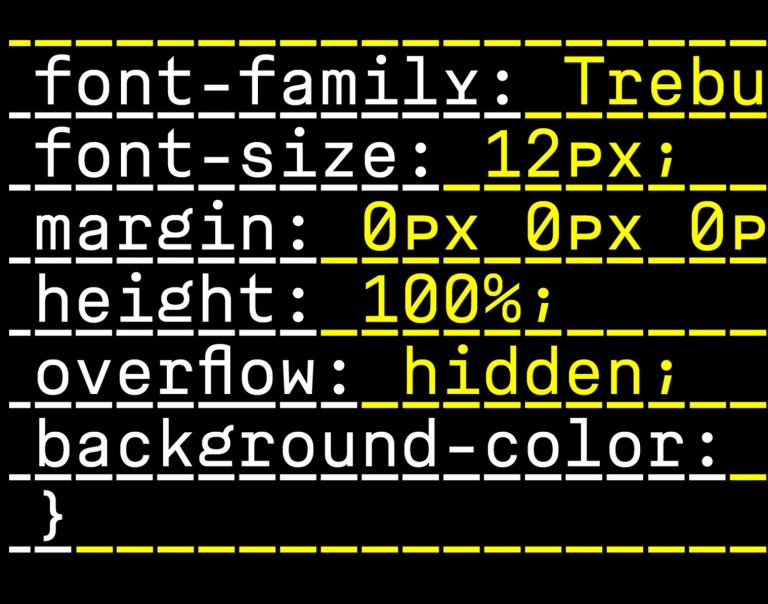
Tipografías monoespaciadas: la irresistible belleza del orden
ASM, diseñada por Íñigo Jerez.
Durante mucho tiempo han sido las letras más serias del mundo tipográfico, pero poco a poco, la percepción que tenemos de ellas ha ido cambiando y parece que ahora se han soltado definitivamente la melena. Pero empecemos por el principio.
Soy monoespaciada y también me divierto.
Ya lo dice su propio nombre: las tipografías monoespaciadas son aquellas cuyos caracteres ocupan siempre el mismo espacio, en contraposición a las tipografías de anchura variable o proporcional, donde los caracteres poseen tamaños diferentes entre sí. Las monoespaciadas encuentran su antecedente en las máquinas de escribir, en las que con cada impresión de letra tecleada el carro avanzaba siempre la misma distancia.
Son las tipografías usadas desde siempre por los programadores debido a que proporcionan gran legibilidad en un entorno donde una nítida identificación de los caracteres es de vital importancia. Por otro lado, en el plano meramente estético, se ha recurrido a ellas para dotar de cierto aire retro a según qué diseños, por ejemplo, rememorar el ambiente de la escritura a máquina de un original de guión de cine clásico.
Ser y no ser mono
Operator, diseñada por Hoefler & co.
Quizá, desde el punto de vista exclusivamente del diseño gráfico, su, digamos, rigidez, ha sido un escollo, aunque, por otro lado, siempre he pensado que aplicadas con gracia y en el lugar idóneo se convierten en una opción irresistible. Y no soy la única que lo piensa. En los últimos tiempos, tanto su diseño como su uso estético están cambiando, o, mejor dicho, están evolucionando y, por lo tanto, ensanchándose considerablemente sus posibilidades y prestaciones. Un muy buen ejemplo de ello viene de la mano de la fundición tipográfica norteamericana Hoefler & Co., que nos sorprendió a principios de este año 2016 con Operator, una tipografía con todo el espíritu de las monoespaciadas, pero sin las limitaciones mecánicas de éstas, es decir, eliminando el ancho fijo y permitiendo que los caracteres adopten sus proporciones naturales. Operator está compuesta por una completa familia opentype de nueve pesos con sus respectivas y sorprendentes cursivas.
Operator es toda una pirueta tipográfica: una monoespaciada que no es una monoespaciada.
Y para completar, aún más si cabe, la jugada, Hoefler & Co. no se han detenido ahí y han puesto la guinda al proyecto aunando las necesidades tanto de diseñadores como de programadores con la Operator Mono, una refinada destilación de las monoespaciadas puras que resulta perfectamente idónea para programar con estilazo o para diseñar matemáticamente.
De la misma manera que las fundiciones están ampliando el abanico de posibilidades de las monoespaciadas manipulando su ADN, los diseñadores están ampliando su utilización en campos donde era poco frecuente encontrarlas, dando lugar a diseños audaces y frescos.
Mi fijación con las monoespaciadas viene ya de lejos, pero se hizo más fuerte gracias al diseño de packaging de la línea de productos Body Luxuries de la marca Suavinex, realizados por el Estudio Mllongo. Me sedujo de ellos la utilización de una monoespaciada junto con una tipo de serifa en mayúsculas en los envases destinados a una línea de cosméticos para bebés y mamás, combinación nada habitual en este tipo de productos.
Línea de packaging Body Luxuries de Suavinex diseñada por Estudio Mllongo.
Packaging Body Luxuries de Suavinex diseñada por Estudio Mllongo.
El resultado, un diseño audaz y memorable, que marca la diferencia con otros productos de su segmento y que, por lo tanto, resulta muy original, pero sin perder, en mi opinión, ni un ápice de dulzura. A partir de ese momento, mi ojo de diseñadora tipópata, ya no podía ver nada más que monoespaciadas por todas partes.
Monoespaciadas everywhere.
Inconsolata, Courier, Apercu Mono, Letter Gothic, Andale Mono, Pica 10 Pitch, Greta Mono, Asm, GT Pressura mono, Pitch… Éstas son algunas de mis preferidas a la hora de combinarlas con otros estilos. Todas ellas me parecen muy versátiles, muy todoterreno. Bien usadas, funcionan realmente bien tanto en diseño web como en diseño de marcas, en diseño editorial y, como hemos visto, pueden quedar estupendamente en packaging. Vamos a verlo por partes.
Personalidad mono
A pesar de lo inquebrantable en su espaciado, la estética de una monoespaciada, esa supuesta rigidez que decía un poco más arriba, puede ser una gran ventaja y resultar absolutamente comunicativa, llegando a expresar de manera precisa y clara lo que la marca necesita para diferenciarse.
Aire web
Que la legibilidad de las fuentes monoespaciadas resulta vital en programación ya lo sabíamos, pero servidora desconocía la importancia de las ligaduras para mostrar caracteres más «entendibles» para los desarrolladores de código. Gracias a que mi trabajo como diseñadora me ha dado la oportunidad de colaborar estrechamente con excelentes programadores, he aprendido a valorar la necesidad de tipografías monoespaciadas adaptadas a quienes manejan diariamente grandes cantidades de código, es decir, grandes cantidades de caracteres diferentes.
Por otro lado, cada día más, el diseño web tiende a la claridad, la nitidez y la limpieza, por lo tanto, una fuente monoespaciada puede cumplir la doble función estética y funcional. Diseños con mucho aire, minimalistas, que no saturen visualmente, esto se puede conseguir con este tipo de fuentes.
En resumen, las monoespaciadas, a pesar de su aspecto serio y formal, son unas seductoras natas, y, encima, aptas para todos los públicos y combinan a la perfección con todo tipo de letra. Ya es hora de romper clichés y salir de la encorsetada idea de que son demasiado rígidas o solo sirven para código. Adelante, sé valiente y dales la oportunidad que se merecen, porque, queramos o no, ya se han ganado su lugar en el diseño y piensan quedarse.